通常海报设计是以图形+文字结合,两者相互相成,图形化的设计看起来会比较美观,并更容易吸引用户的眼球,然而也有例外,有些海报是以文案为主题,即以文字是是海报的主体,图像只是辅助的作用。
也许,有些设计师认为单单以文字作为海报的主体就会显得单调,这样的海报能吸引用户吗?我想你看了今天我们分享的文字海报设计作品后,你会大有改观。
下面的海报设计作品均是以文字为主体的设计元素。这些文字经过设计师的精心排版、设计修饰,就变成了一幅幅美丽的海报,话不多说,我们直接看图。
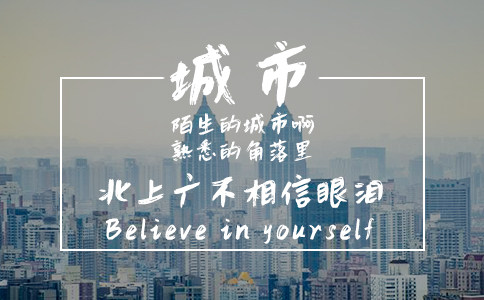
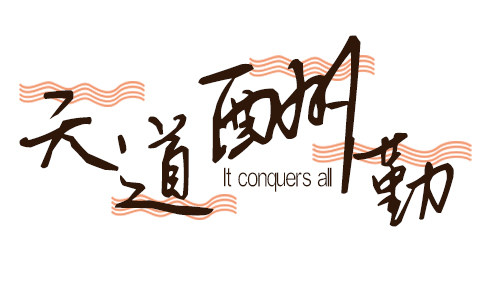
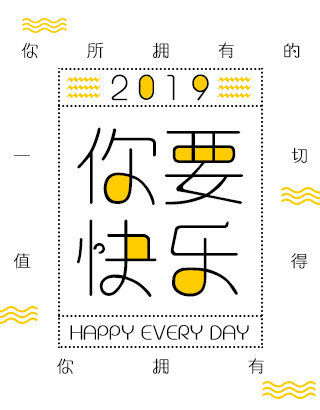
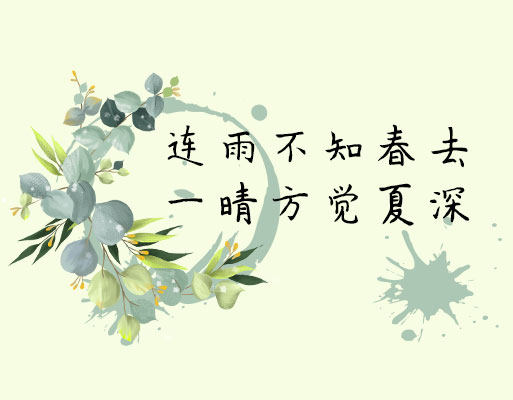
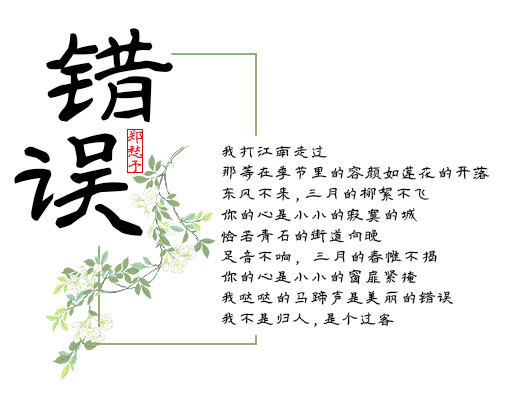
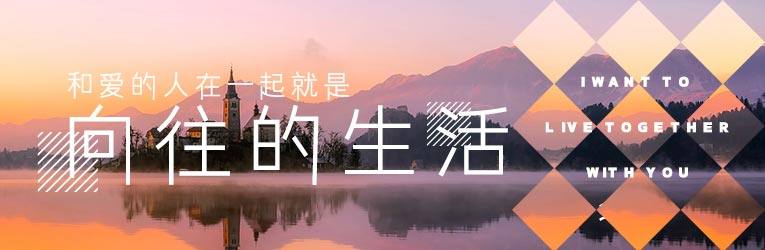
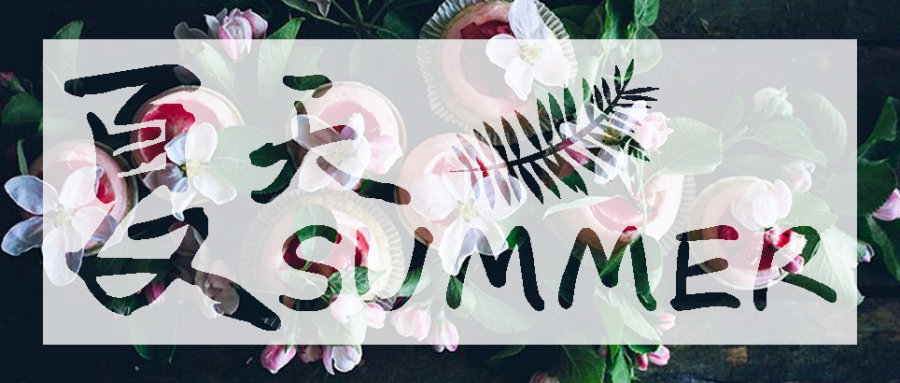
用文字贯穿画面,也是一种设计套路。是不是这样的设计让文字显得更有魔力了呢。